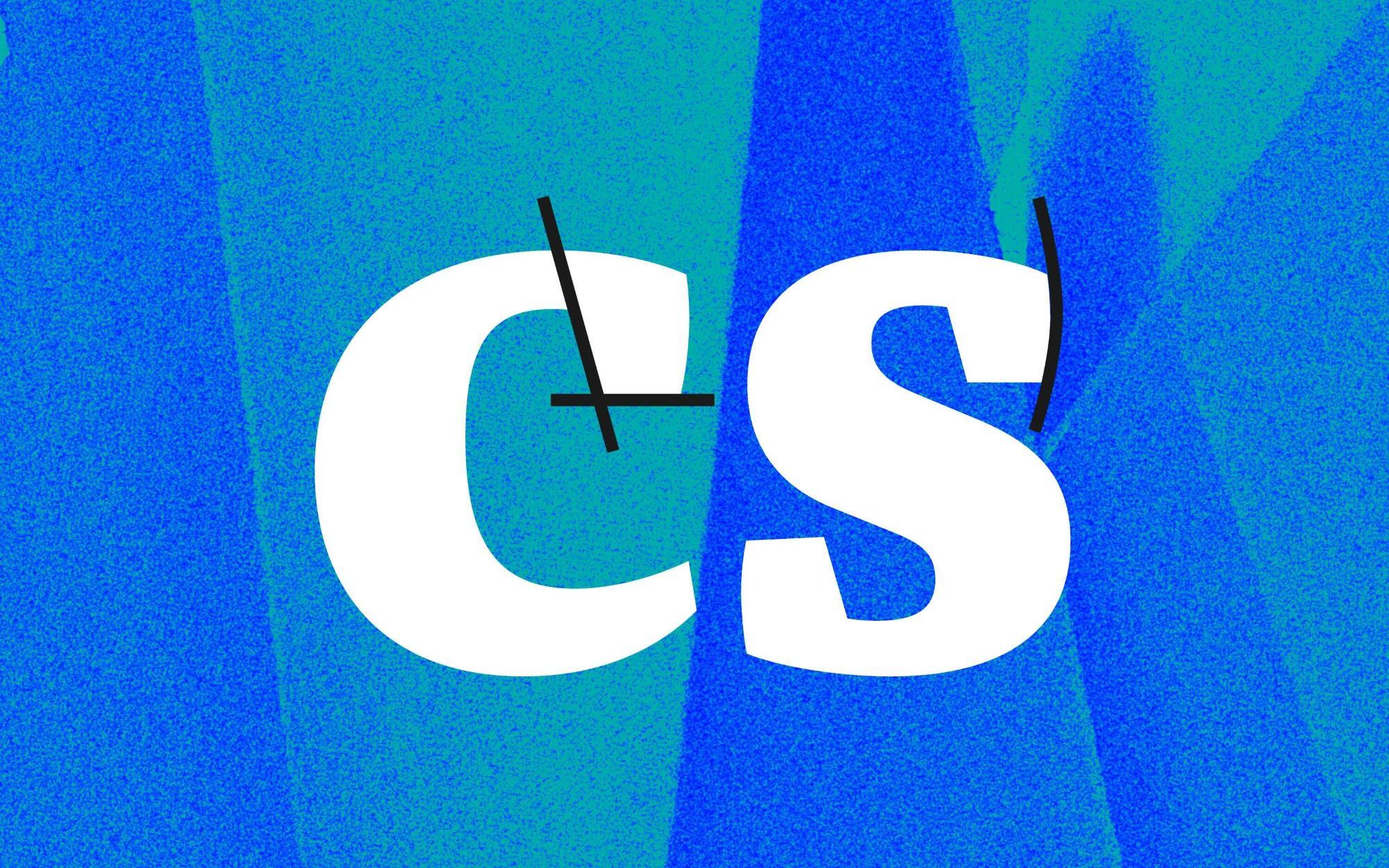
- 2014
- Antiqua humanistisch
- Versaleszett:
- enthalten
Die Franziska von Jakob Runge wurde an der »Muthesius Kunsthochschule« in Kiel unter der Leitung von Albert-Jan Pool und Prof. André Heers im Jahr 2012 als Masterarbeit begonnen. Ab 2013 wurde die Schrift für die FontFont-Bibliothek ausgebaut und verfeinert. Sie erschien dort im Juni 2014.
Der kräftig-robuste Schriftentwurf spielt mit einer Mischung von Antiqua- und Egyptienne-Elementen. Die Kursive ist nur leicht geneigt und zeichnet sich durch ihren kräftigen, scharfkantigen Schnitt aus. Eine Reihe von Piktogrammen, einschließlich verschiedener Pfeile und Dingbats, ergänzen den üblichen Zeichenumfang.
Die Familie ist in 10 Strichstärken (Hairline bis Black) in aufrechten und kursiven Schnitten erhältlich.
Seit 2024 wird die Schrift exklusiv über TypeMates vertrieben. Dazu hat Antonia Cornelius die Schrift nochmal hinterfragt, an den TypeMates Produktionsstandard angepasst und Variable Fonts aufgesetzt. Die Schrift-Daten blieben aber weiterhin kompatibel mit der bewährten FontFont-Version.
Der komplette Entwicklungsprozess der Franziska – von Konzept über Skizze bis Font-Produktion – ist hier nachzuvollziehen typemates.com/news/making-of-franziska